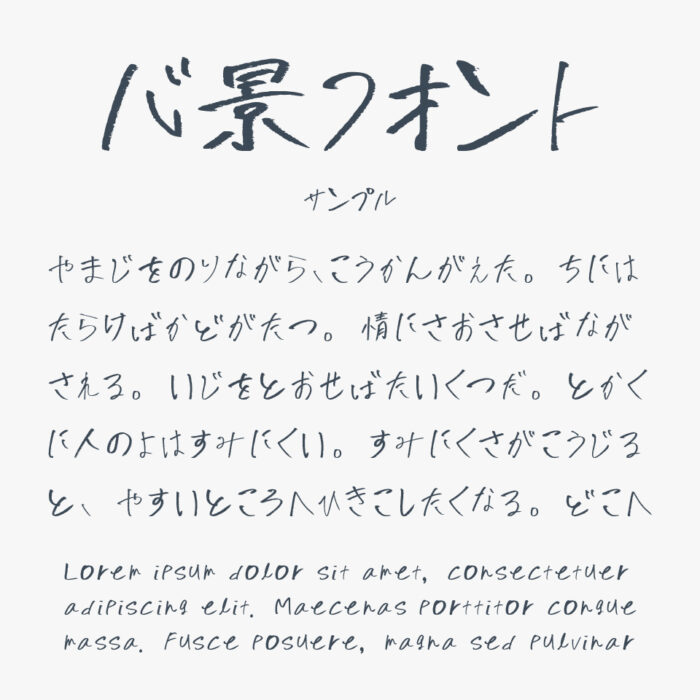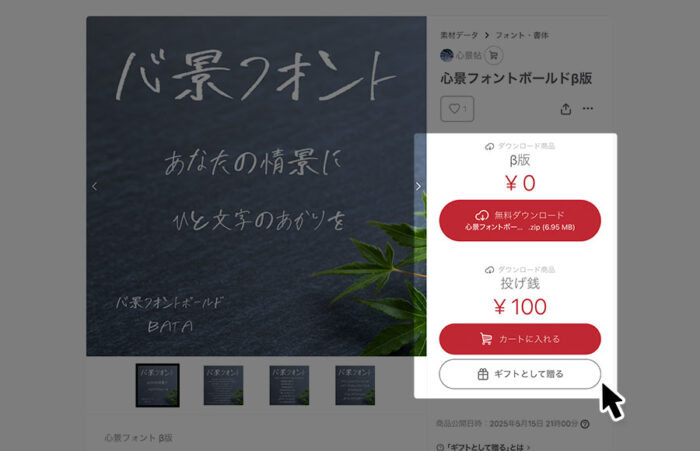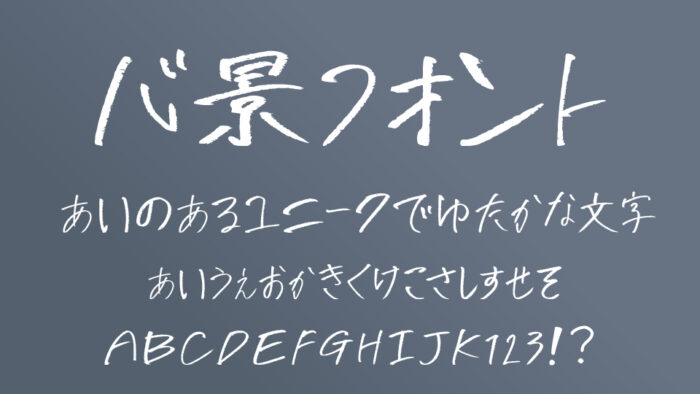
心景フォントは、筆ペンのような繊細でかすれた筆跡が印象的な手書きフォントです。
手書き感のある文字は均一ではなく、感情のゆらぎが表現されている雰囲気を感じるフォントです。詩やエッセイ、心情を表現する文章にぴったりで、静けさや余韻を感じさせたい場面にぴったりな手書きフォントです。
収録文字は、漢字(平家物語冒頭に出現する文字まで)・ひらがな・カタカナ・アルファベット・数字・記号が収録されています。